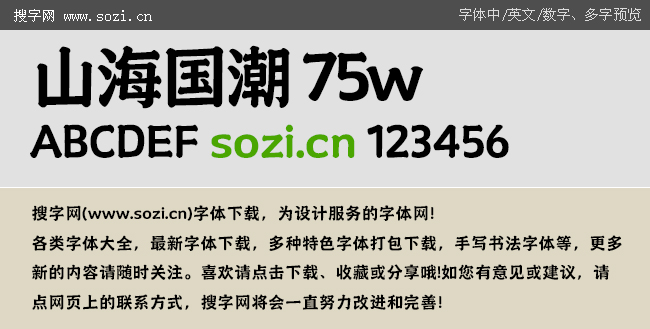
山海國(guó)潮 75w
搜字網(wǎng)給大家提供一款山海國(guó)潮 75w中文字體下載,山海國(guó)潮字體是一款充滿(mǎn)古典韻味的字體,這款字體的特點(diǎn)是筆畫(huà)簡(jiǎn)潔流暢,字形端正大方,有一種古樸而莊重的感覺(jué)。適用于畫(huà)冊(cè)設(shè)計(jì)、海報(bào)設(shè)計(jì)、包裝設(shè)計(jì)等場(chǎng)合使用。
- 風(fēng)格類(lèi)別: 楷體